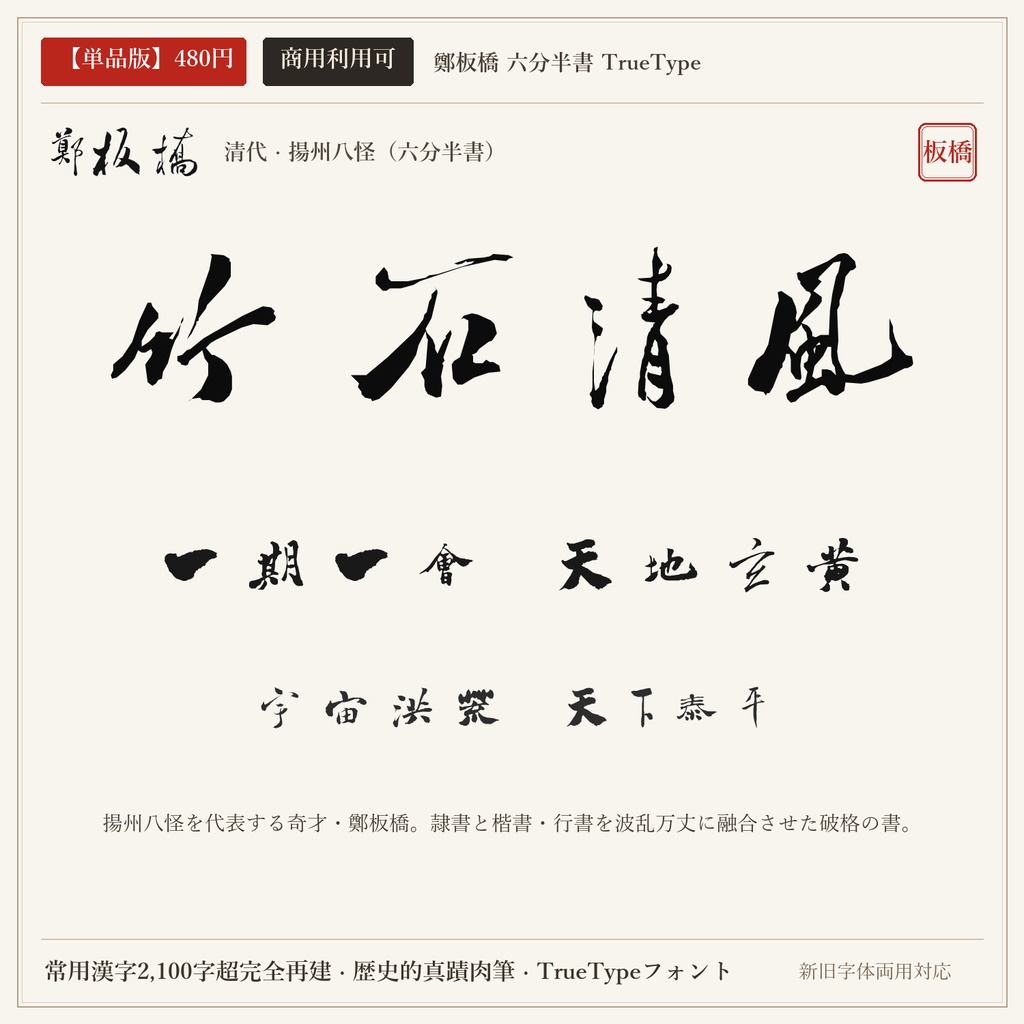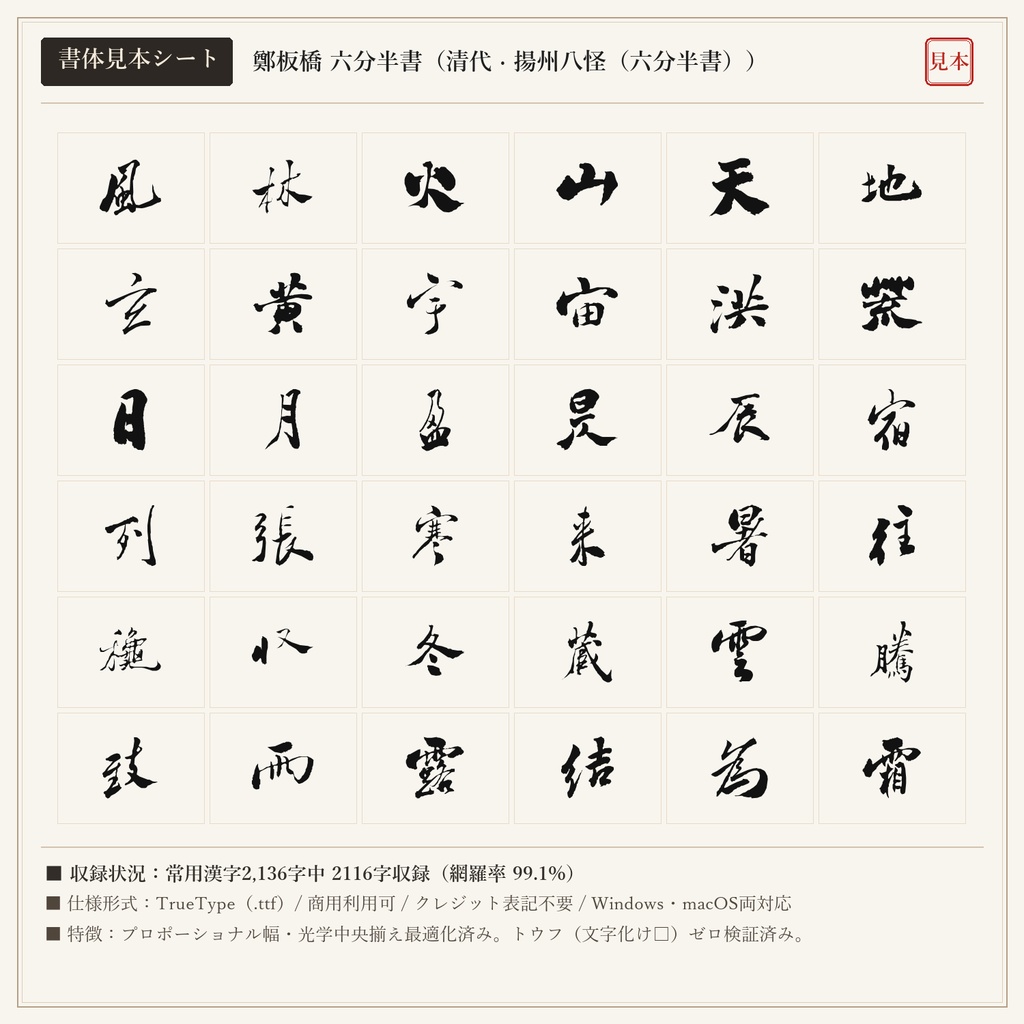
【単品版】鄭板橋 六分半書フォント|隷楷合体の破格美・難得糊塗・商用利用可
清代中期の鬼才・鄭燮(板橋)が創始した唯一無二の「六分半書(板橋体)」から制作したフォントです。隷書の平らな広がりと楷書の骨格、行書の波打つリズムを融合させた、ユーモラスで洒脱な書風です。 ■ 本フォントの特徴 ・常用漢字2,136字中、2116字を高精度収録(網羅率 99.1%)。 ・現代の新字体を入力しても、歴史的な真蹟字形・旧字体が自然に出力されるデュアルマッピング対応。 ・文字ごとの最適なプロポーショナル字幅設定により、自然で流麗な連綿と墨の息遣いを再現。 ・トウフ(文字化け□)を出さない事前フォントマッピング検証済み。 ■ 未収録文字一覧(全20字) 歴史的真蹟・拓本に存在しない以下の字種は未収録(非対応)となります。ご購入前にご確認ください。 丼 刹 咲 唄 堀 峠 拶 枠 栃 桁 濫 疎 線 脊 菓 著 込 郷 闘 駄 ■ 形式 TrueTypeフォント(TTF) / Windows・macOS両対応 ■ 利用規約 個人・法人の商用利用OK。クレジット表記不要。 ロゴ、動画、ゲーム、書籍、同人誌、配信サムネイル、Web、印刷物、グッズ等に自由にご使用いただけます。 フォントファイル自体の再配布・共有・販売・転売は禁止です。 ※東晋の王羲之(行書)と盛唐の顔真卿(楷書)を同梱した「【無料版】王羲之 + 顔真卿 2書体セット(0円)」もショップ内にて無料配布中です。